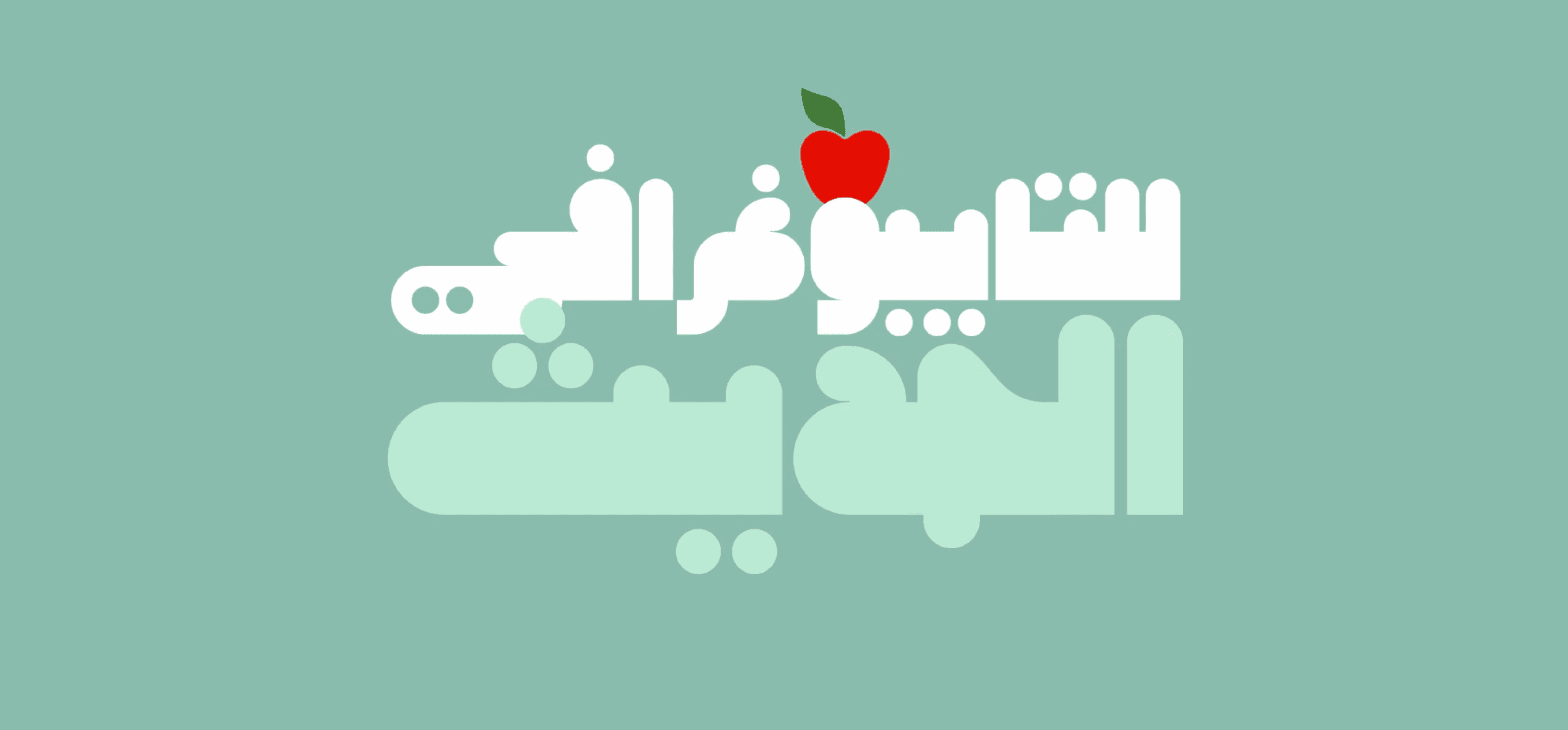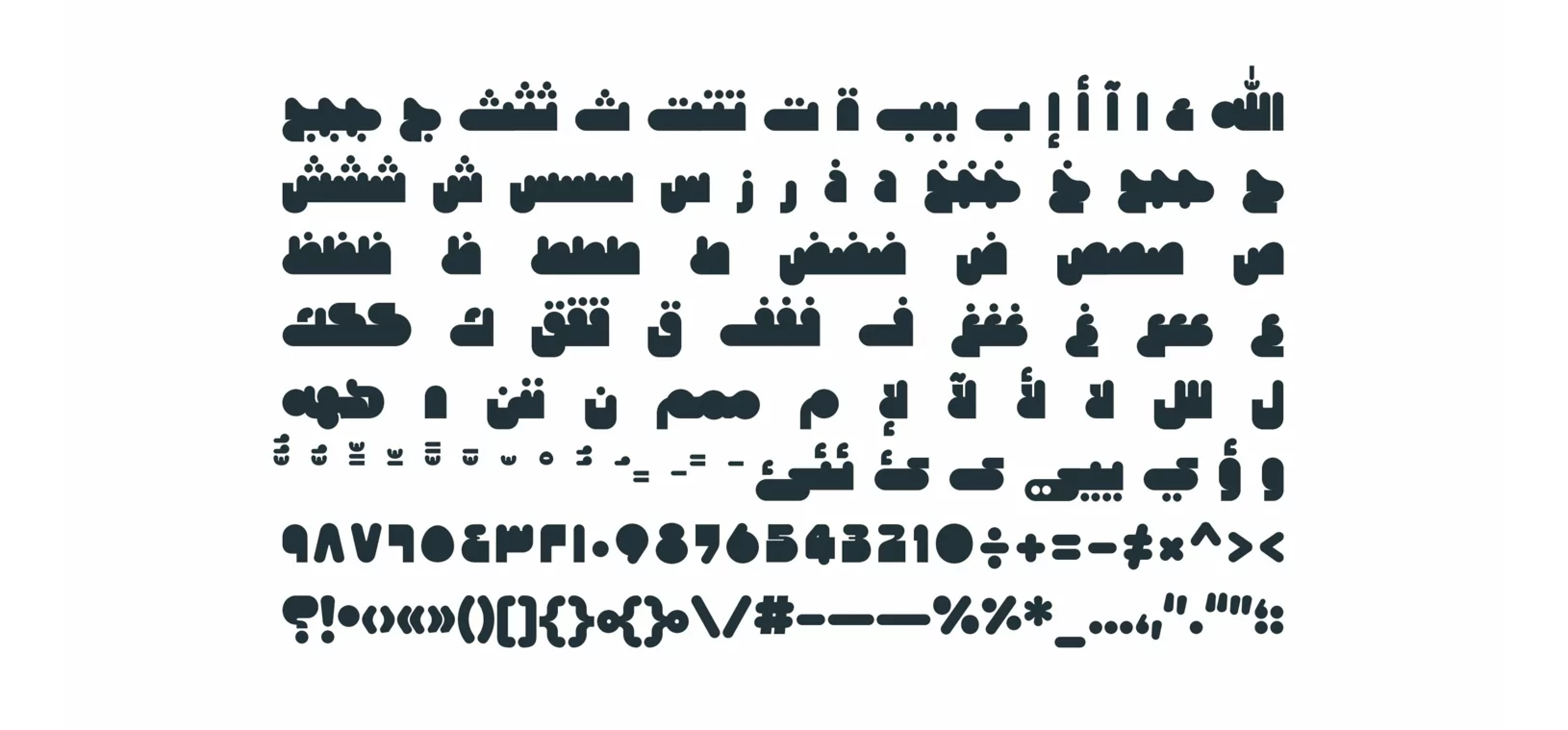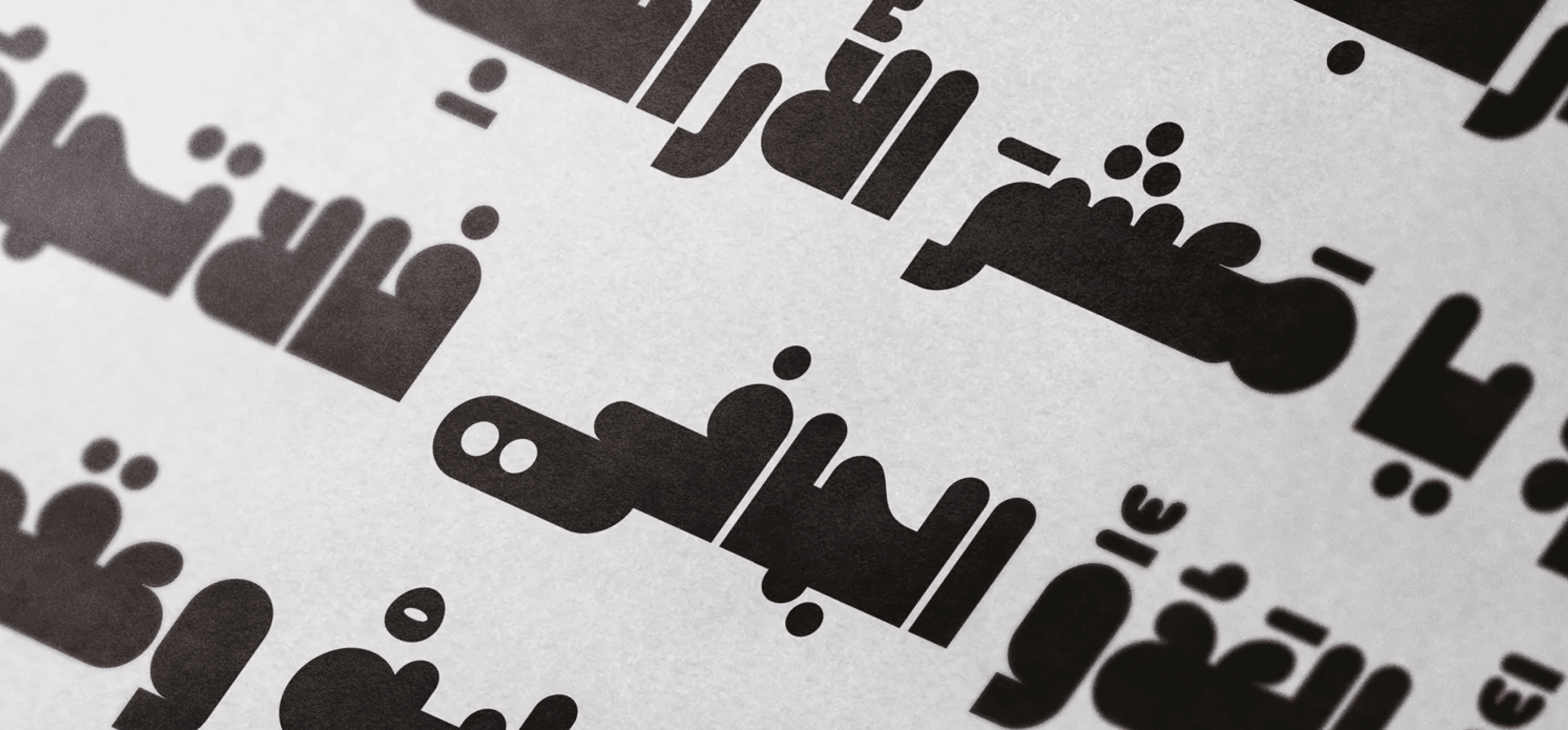
خط حواديت – Hawadeet Arabic Font
"حواديت" هو خط عرض عربي مستوحى من الكلمة العامية التي تعني "القصص الخيالية"، يتميز بتصميم ثقيل للحروف ونهايات دائرية ناعمة تمنحه طابعًا ودودًا ومميزًا.
يُعد مثاليًا للعناوين الإبداعية، تصميم المنشورات، مشاريع الطباعة، والهويات البصرية الجذابة.